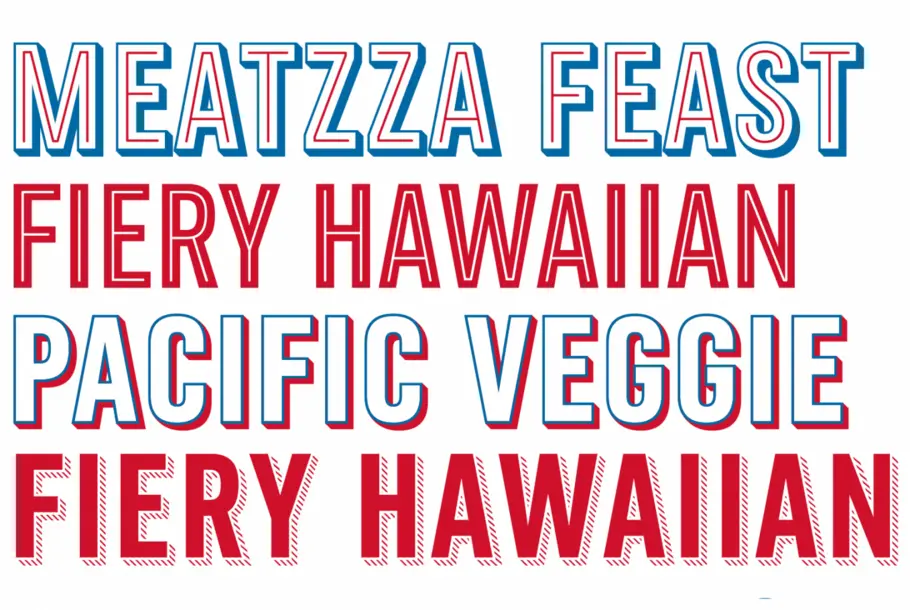
用于达美乐比萨的可堆叠字型。
Monotype设计师Terrance Weinzierl通过他模块化、多种字重的Pizza Press字型,为达乐美带来了现代美式的风味。
Weinzierl为响应Crispin Porter + Bogusky为达乐美制作简介而进行创作,他的任务是创作一种会引入“当代”感的字型,同时要与已经在使用的Trade Gothic®设计搭配得当。通过创作一系列可以多种方式堆叠的模块化字体,Weinzierl的设计减轻了品牌字体设计的负担,也可以让设计师和门外汉引导他们内部的字体设计师。
Pizza Press字型基于19世纪的模型,并参考了现有的Trade Gothic®字型。其他历史性参考资料有助于为设计提供信息,Weinzierl研究了细致的金属字体标本,以了解这些微小而类似射线的条纹在过去是如何被创作出来的。Gill Sans® Shadow字体也是一个技术参考点,Weinzierl解释说,“像这样的阴影设计需要一些不寻常的光学调整。”这就意味着每个阴影字重的纵沟纹上条纹的角度和间距都是手工调整的。其他详细的考虑包括从G中消除杂散,以确保字母形状可以承受行内字重。
该设计还包括内置的墨水陷阱,其轮廓字重与阴影字重以一根头发重叠,以确保在屏幕上渲染时背景颜色能显示出来。Weinzierl还制作了仿古条纹字重的光学变体(常规和显示),可在各种尺寸和印刷环境中使用。
“ “将一个非常费时费力的过程——手动复制轮廓的矢量图并粘贴到布局中,变得就像在键盘上打字一样简单,这毫不夸张!” ”
正是这种级别的对细节的理解和关注,促使Crispin Porter + Bogusky与Monotype合作,CP+B的数字资产经理Jake Harvey说:“我们对Monotype在字体设计方面工作的悠久历史充满信心,它对“细微之处”的理解程度很高,因此最终产品保留了原始设计的特征和精神。”字型还提供了简化和变化,用Harvey的话说,“将一个非常费时费力的过程——手动复制轮廓的矢量图并粘贴到布局中,变得就像在键盘上打字一样简单,这毫不夸张!”
该字型已经用于包装、标牌和电视广告,并将继续部署在任何使用多乐美品牌的环境中。Pizza Press在2014年还获得了TDC字型设计卓越证书。